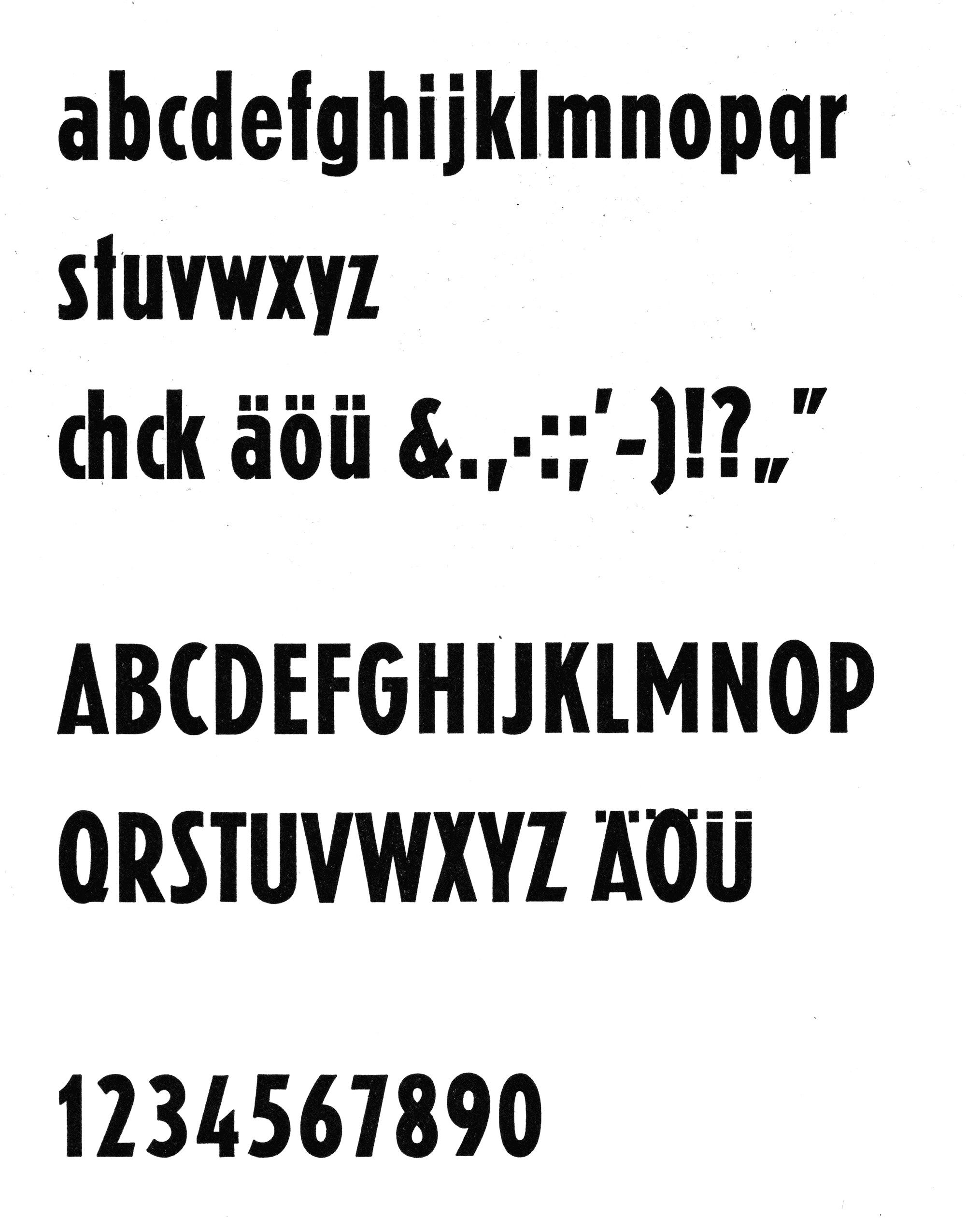
Siemens Ziffern und Kleinbuchstaben - welche Schrifttype kann das sein?
Die Siemens Firma Klangfilm GmbH hat in den 50er Jahren Stempel verwendet um Holzteile zu kennzeichnen.
Die Numerierung umfaßt meines Wissens nur die Ziffern 1 .. 4 und Kleinbuchstaben a .. h.
Die Schrift ist recht altertümlich und hat keine offensichtliche Ähnlichkeit zu dem was man so kennt.
Sehr wahrscheinlich gar keine benannte Schrifttype, da aus einer Zeit stammend, in der benannte Schrifttypen nahezu ausschlichlich im Druckgewerbe als Bleilettern genutzt wurden, alles andere hingegen direkt für die jeweilige Anwendung gezeichne wurde, ohne dass die Schrift dann einen Namen bekam. Dies hier war dann eben irgend eine "Blockschrift" eines anonymen Stempelherstellers. Das Schrifttypen einen Namen haben, begann außerhalb des Drucks von Bleilettern erst mit dem Aufkommen von Abreibe-Buchstaben von z.B. Letraset, und selbst in dieser Zeit bestellte man seinen Stempel nach meht oder weniger geneerisch benannten Mustern als Block- Schreib- oder Kursivschrift, wie es der jeweilige Stempelhersteller halt gerade anbot, die jeweilige Auswahl war da zumeist sehr eingeschränkt, und von Anbieter zu Anbieter regional unterschiedlich.
Das sieht für mich sehr nach der schmalfetten Erbar aus. Ich meine dabei aber die alten Originale und nicht die moderenen Remakes von URW und anderen Herstellern. Bei denen ist die 4 anders, also geschlossen.
Siehe Abschnitt: Schriftschnitte der Schriftart „Erbar“
Ich glaube aber, da stimmt die 4 nicht mehr? Hier wurde das diskutiert und einige Schriften dieser Art vorgestellt (Die Neu5land im Bild passt nicht so ganz, hat aber die richtige 4):
"Hausschrift Siemens", aber da sehe ich nichts, womöglich geht es auch nur um
den Firmennamen als Logo-Schrift.
Bei einer Hausschrift geht es in der Regel um die Schrift, mit der eine Firma ihre hauptsächliche Korrespondenz (Werbung, Schriftverkehr) erledigt. Stempel für die Produktion in dieser Schrift zu gestalten, ginge weit über das hinaus, was man an Corporate Identity/Design machen würde.
Erbar, das sieht sehr gut aus. Ich hatte mir schon mal die ersten Seiten
der alphabetischen Liste hier durchgesehen, aber es sieht dann anders
aus, wenn die schmalen und fetten nicht mit abgebildet sind, obwohl
das als Beispiel verwendet kleine a doch recht charakteristisch ist.
Auf einem der Bilder sieht man, dass der gerade Strich bei "b" viel kürzer
ist, so was kann man jedoch ändern ..